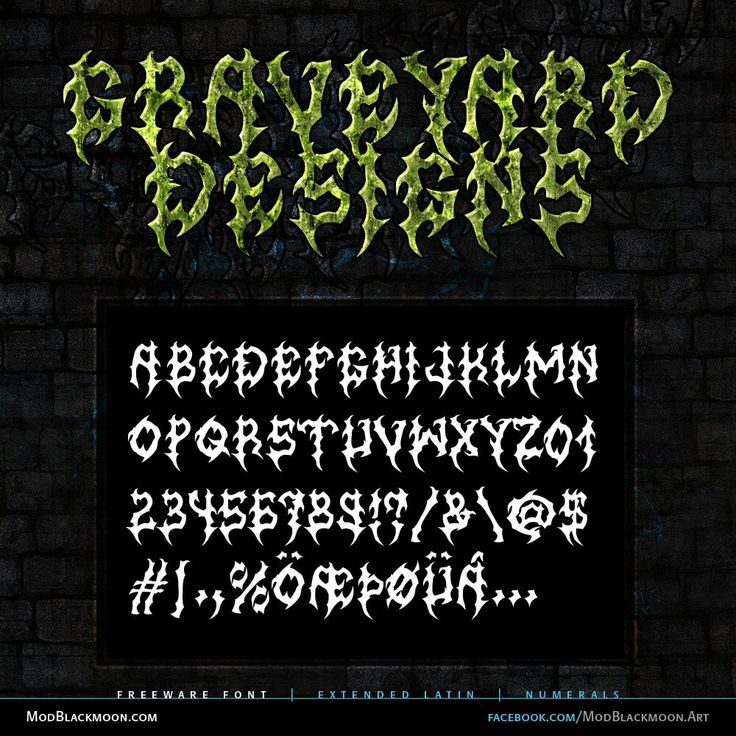
Демонические Шрифты, Death Metal Шрифты, Футуристичные и Индустриальные Метал Шрифты
MB Slavonic Minsk — Славянский Средневековый Металл Шрифт
Славянский шрифт, отрисован вручную в восточно-европейском средневековом стиле под кириллицу, подходит для Folk Metal групп. Включает расширенный Латинский (Английский) алфавит, Кириллицу (Русский) и цифры. Бесплатный для частного использования, для коммерческого необходима ссылка на сайт автора. Создано: Сентябрь 2010
Шипованный, грубый, расколотый шрифт в стиле надписей из комиксов на тему ужасов.
MB Gravitation — Граффити Шрифт
Шрифт в стиле граффити, гладкие края, жирный и хорошо читаемый. Я обычно не работаю в этом стиле, но захотелось попробовать что-то необычное, и добавить разнообразия в мою коллекцию Металл Шрифтов. Включает расширенный Латинский (Английский) алфавит, Кириллицу (Русский) и цифры. 100% Бесплатный, ссылка на сайт автора приветствуется. Создано: Август 2010
Футуристический инопланетный шрифт с линиями и кругами для арта или дизайна интерфейсов и панелей управления космического корабля, со своей яркой инопланетной индивидуальностью. Включает расширенный Латинский (Английский) алфавит и цифры. 100% Бесплатный, ссылка на сайт автора приветствуется.
MB Graveyard Designs — Современный Брутальный Death Metal Шрифт
Брутальный и злобный Металл Шрифт, подходит также для дизайна надписей в Black Metal стиле. Создан для использования в названиях и заголовках, так как не очень хорошо читаем в мелком размере. Включает расширенный Латинский (Английский) алфавит и цифры. 100% Бесплатный, ссылка на сайт автора приветствуется. Создано: Июль 2010
Рукописный, нацарапанный металкор шрифт. Подходит для стилизации текста в пост-апокаллиптическом стиле. Включает расширенный Латинский (Английский) алфавит, Кириллицу (Русский) и цифры. 100% Бесплатный. Создано: Август 2010
Зловещий разъеденный шрифт для создания футуристического дизайна, текстов инопланетян, панелей космического корабля.
MB Lords of Evil — Демонический, Дьявольский Металл Шрифт
Демонический Black Metal шрифт, созданный под вдохновением графики и логотипа классической ролевой игры Diablo 2. Отрисован карандашом вручную. Включает расширенный Латинский (Английский) алфавит и цифры. 100% Бесплатный, ссылка на сайт автора приветствуется. Создано: Март 2010
Современный готичный металл шрифт в крючковатом адском стиле, лучше детализирован чем более ранние шрифты. Отрисован вручную карандашом под вдохновением ролевой игры Diablo. Включает расширенный Латинский (Английский) алфавит и цифры.
MB An Old Witch — Нацарапанный Металкор Шрифт
Вручную нацарапанный шрифт, стилизованный под рукопись ведьмы. Хорошо читаемый в мелком размере и может быть полезен для оформления треклиста металкор группы или надписей для фентезийного проекта. Включает расширенный Латинский (Английский) алфавит, Кириллицу (Русский) и цифры. 100% Бесплатный. Создано: Сентябрь 2010
Скачать Нацарапанный Шрифт An Old Witch на daFontThe Great Reaper — Злобный Death Metal Шрифт
Полностью бесплатный шрифт в стиле Death Metal группы. Основная форма стилизована как косы Жнеца. Отрисован вручную карандашом. Включает расширенный Латинский (Английский) алфавит и цифры. 100% Бесплатный, ссылка на сайт автора приветствуется.
Используется официально группой: Wayfarer (Загреб, Хорватия). Создано: Апрель 2010
MB Back For Death — Расколотый Гранжевый Метал Шрифт
Все края разъеденные и потертые, что делает шрифт давольно высоко детализированным, но все еще достаточно хорошо читаемым в мелком размере. Созданы как заглавные так и строчные буквы. Включает расширенный Латинский (Английский) алфавит, Кириллицу (Русский) и цифры. 100% Бесплатный. Создано: Январь 2010 Скачать Гранж Шрифт Back for Death на daFont 50 бесплатных готических шрифтов — Клуб 431
подойдёт для Хэллоуина.